Шрифты в вебе
Font Face
95% информации
в вебе — текст.
Все шрифты отличаются между собой. Для удобства работы, шрифты принято разделять на семейства.
Можно особо выделить
три семейства шрифтов
Семейства шрифтов
Шрифты данного семейства отличаются засечками на концах букв, по причине чего кажутся более величественными и значимыми.
Семейство шрифтов с засечками (serif)
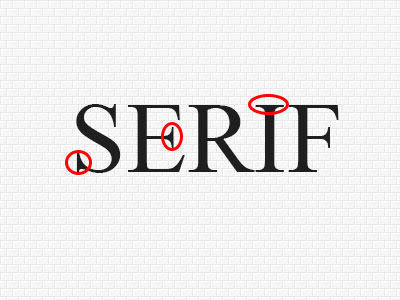
самым узнаваемым представителем данного семейства является шрифт Times New Roman, корни которого уходят аж в 30-е годы прошлого столетия.
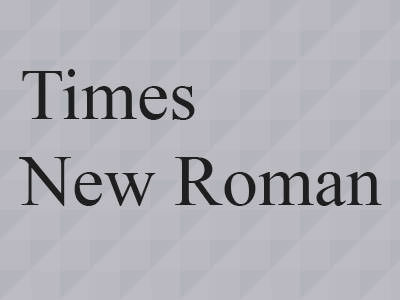
К данному семейству также относятся шрифты:
- Georgia
- Book Antiqua
- New York
Антагонистом предыдущей группы является семейство шрифтов без засечек. Представители данного вида отличаются собранностью и аккуратным внешним видом.
Семейство шрифтов без засечек (sans-serif)
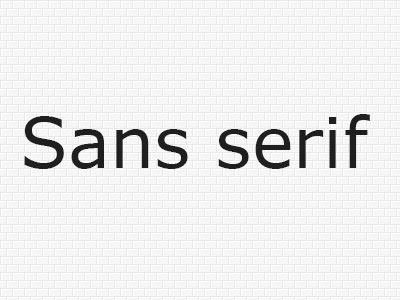
Наиболее яркие представители семейства без засечек:
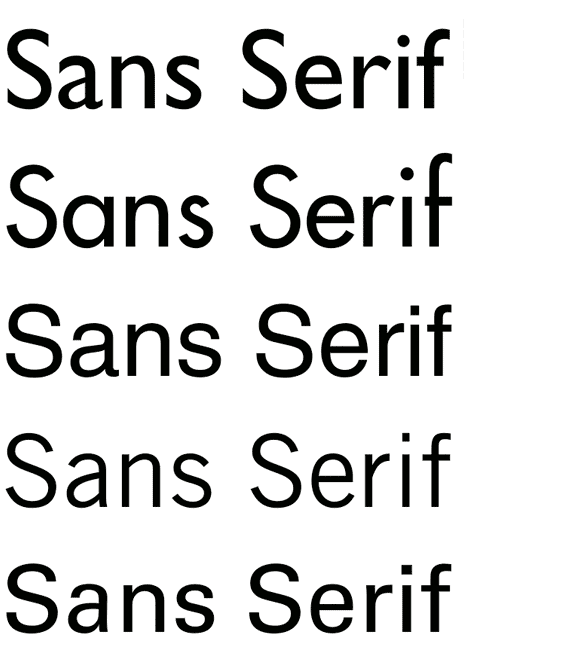
Я предпочитаю использовать данный вид шрифта для основного текста сайта. Идеальный вариант для большого объема текста.
- Arial
- Verdana
- Tahoma
- Helvetica
Моноширинные шрифты отличаются от всех других тем, что у них ширина каждой буквы одинакова. Очень часто эти шрифты используются в коде, ведь одинаковая ширина букв помогает не запутаться в синтаксисе.
Группа моноширинных шрифтов (monospace)
Семейство шрифтов в CSS
}шрифт с засечками
шрифт без засечек.
Как это работает?
}Браузер проходит по списку слева направо и использует первый найденный в системе шрифт.
шрифт без засечек.
Что это значит?
}Условием отображения заданного вами шрифта в CSS файле является то, чтобы он был в наличии на компьютере пользователя. В противном случае, заданный вами шрифт будет заменен браузером на тот, который стоит по умолчанию, а зачастую это — Times New Roman.
Такое положение дел не кажется совсем уж радужным, ведь откуда вам знать, какие шрифты есть на устройствах пользователей?
Но, не стоит расстраиваться, так как каждая операционная система имеет стандартные, предустановленные шрифты.
Безопасные шрифты
(web-safe fonts)
Предустановленные на операционных системах шрифты принято называть безопасными.
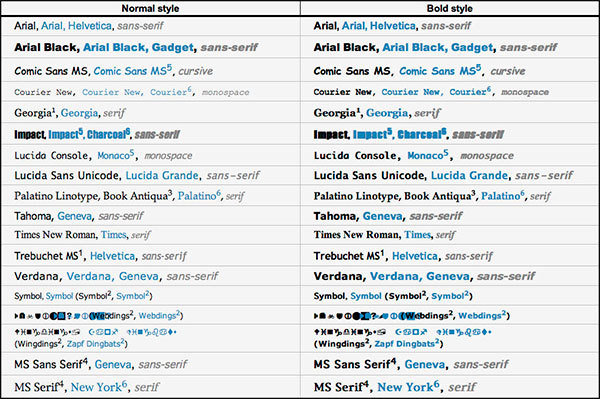
Все безопасные шрифты двух наиболее популярных операционных систем (Windows и Mac OS)
На практике, в свойстве font-family мы указываем оба варианта через запятую.
}Однако, у вас может возникнуть необходимость в использовании других, более экзотических шрифтов, которые, скорее всего не установлены на компьютерах пользователей.
Нестандартные шрифты
(custom fonts, веб-шрифты)
Нестандартный шрифт в отличии от стандартных — это шрифт, который с большой вероятностью будет отсутствовать у большинства посетителей сайта.
Нестандартные шрифты в CSS подключается через @font-face
}Нестандартные шрифты в CSS подключается через @font-face
- В параметре font-family нужно указать название шрифта (не начертания!). Это семантически верно и очень удобно, вместо того, чтобы указывать нечто типа pt_sans или my-ptsans-font.
- Параметры src должны содержать пути до шрифтов разнообразных форматов, чтобы обеспечить кроссбраузерность. Для формата SVG, через символ #, необходимо указать начертание подключаемого шрифта. В нашем случае это PT Sans Regular (если бы мы подключали жирное начертание, эта строка выглядела бы как PT Sans Bold и т.п.)
- В параметре font-weight нужно указать жирность шрифта. Самые распространённые значения: normal и bold. Но можно указать и другие, согласно спецификации CSS.
- Параметр font-style сообщает, является ли шрифт курсивным. Если это так, укажите italic. Если нет — оставьте normal
Google Fonts
Одним из самых популярных и удобных сервисов является Google Fonts. Сервис имеет простой пошаговый интерфейс с возможностью выбора начертаний, языка и метода подключения шрифта (добавьте в свой код одну строку, и вот на сайте уже новый шрифт!).
webfont-генераторы
Если у вас есть файл шрифта, и вы хотите его использовать на сайте, без специальных генераторов не обойтись.
- middle — по середине;
- bottom — по нижнему краю;
- baseline — по базовой линии (значение по умолчанию).
text-shadow: тень текста
}- свойство text-shadow применяется к тексту;
- форма тени повторяет форму текстовых символов;
- можно управлять смещением тени, её цветом, а также размытием;
- нельзя управлять растяжением текстовой тени;
- можно создавать множественные тени.